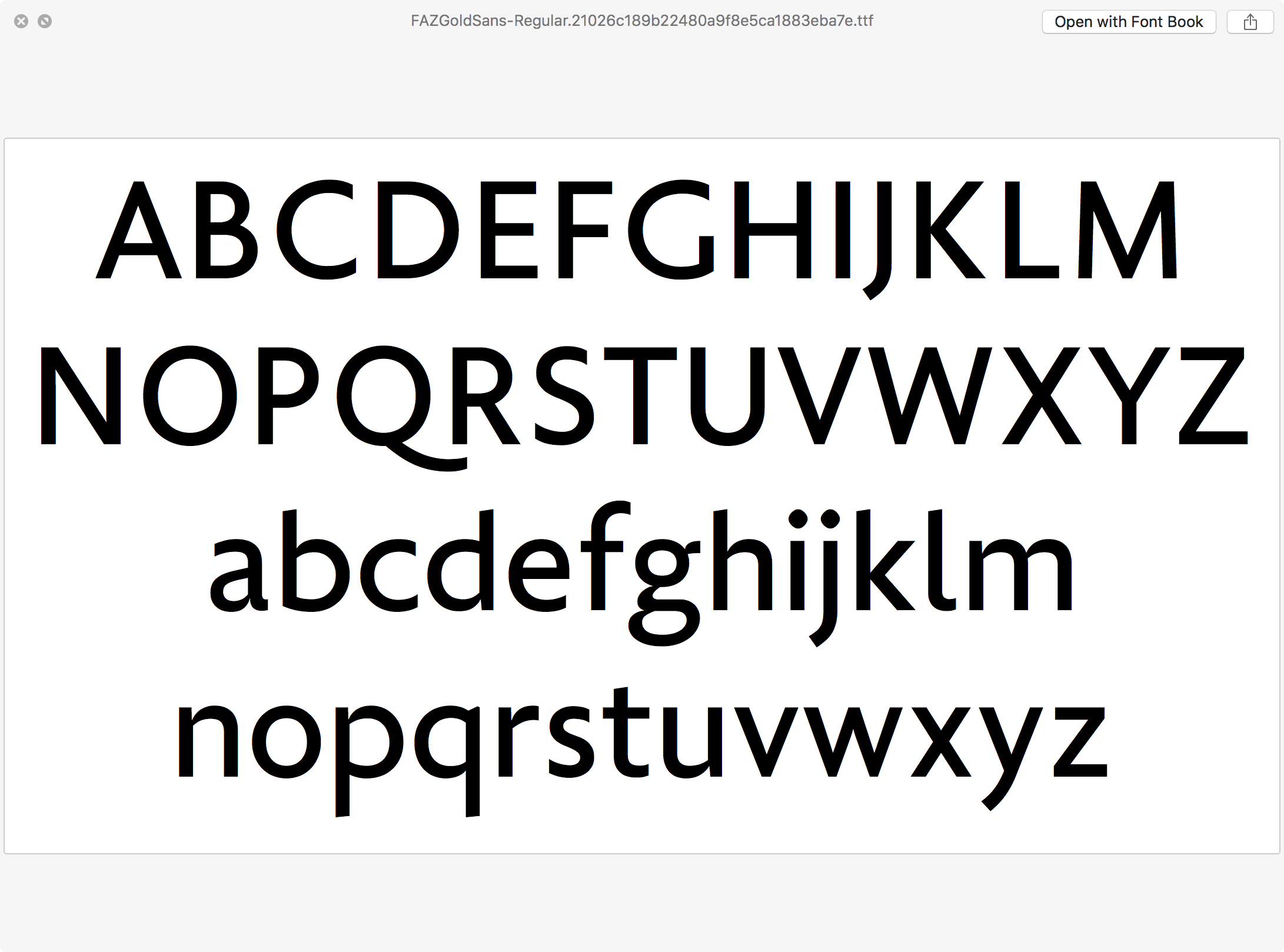
FAZ.net
Mir sprang die dürftige Grundschrift sofort ins Auge. Eine öde Helvetica, die natürlich auch noch viel zu eng steht.
Unter Qualität stelle ich mir was anderes vor.
Dies ist mit meinem veralteten Safari (6) betrachtet:
Und dies mit meinem halbwegs aktuellen Firefox:
Ich sehe in Opera, Firefox und Internet Explorer die „FAZ Gold Sans“.